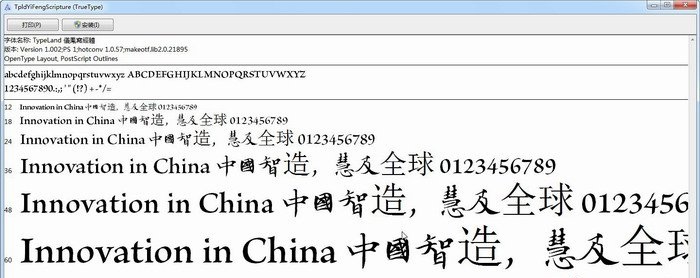
儀鳳寫經(jīng)體字體是一款非常好看的中文字體,風(fēng)格各異、適用于廣告設(shè)計(jì)等方面,有需要的可以體驗(yàn)哦!
儀鳳寫經(jīng)體字體是款大氣磅礴的中文字體。儀鳳寫經(jīng)體字體來源于唐代秘書省所抄寫的金剛經(jīng),該字體效果出眾,風(fēng)格統(tǒng)一,適用于廣告設(shè)計(jì)、印刷包裝等,是設(shè)計(jì)師不可或缺的字體,感興趣的朋友不妨下載看看。